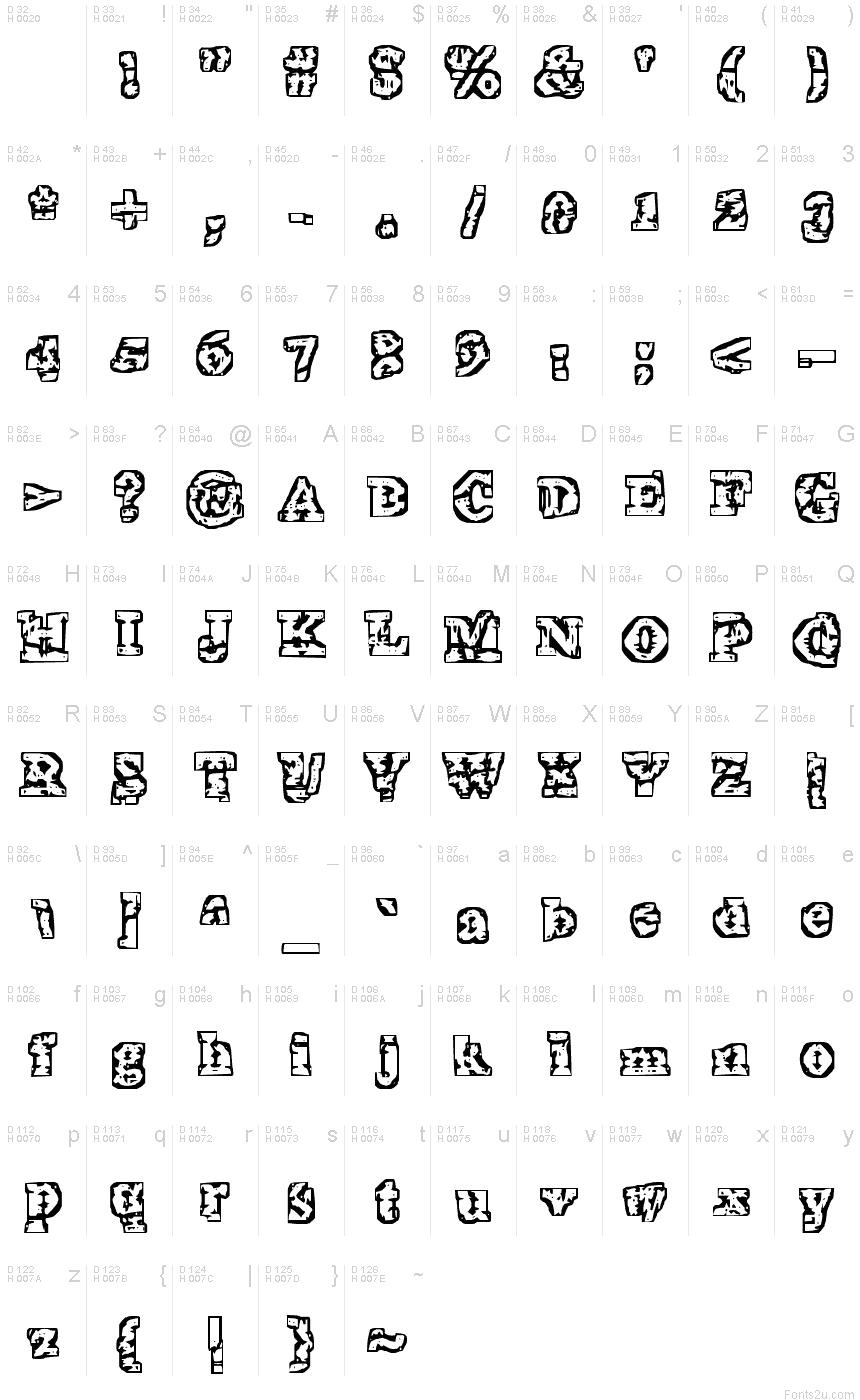
The Interzone od Mr. Fisk je bezplatný distressed display font s drsnou atmosférou pulpové éry. Jeho masivní, blokové znaky vypadají jako osekané a ošlehané časem, s potrhanými okraji a nerovnostmi, díky kterým celé písmo působí jako ošoupaný plakát stržený ze zdi.
Hodí se na ziny, undergroundové hudební letáky, hororové paperbacky, titulky plakátů a herní karty, kde právě tato surová, lo-fi textura hraje hlavní roli. Jakožto bezplatný font skvěle poslouží také na obálky, názvy na obalech a drsný branding, který potřebuje písmena s poškozeným, ručně tvarovaným vzhledem, nikoliv čistou geometrii.